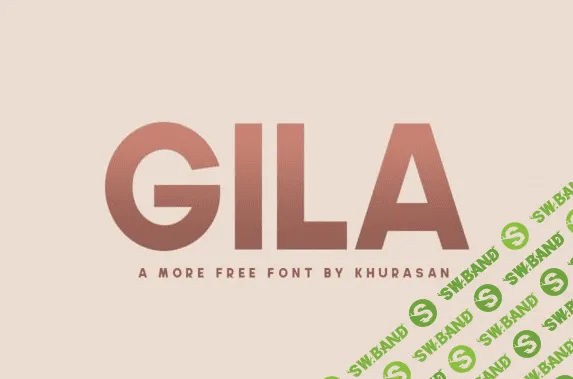
Название: Gila Font
Gila - это современный шрифт без засечек. Он идеально подходит для плакатов, логотипов, журналов, обложек книг, баннеров и многого другого!